스테판 칸체프, 숨은 장인의 발견과 재조명
국내에서 처음으로 일반에 소개된 <스테판 칸체프 그래픽디자인전>은 디자인 대학 에프하 뒤셀도르프(www.design.fh-duesseldorf.de)의 연구기관인 라보어비쥬엘(www.laborvisuell.de)의 프로젝트 <스테판 칸체프의 발견과 재조명>을 하나의 전시로 재구성한 것이다. 스테판 칸체프의 디자인을 소개하는 전시인 ‘로고 룸(Logo Room)’은 디자인 역사의 한 인물을 전기적으로 재조명하고 그의 작업을 재조명하는 것을 목적으로 기획되었다. 전시는 2009년부터 독일, 폴란드, 불가리아 등지에서 선보인 바 있다.
‘로고 룸’에는 오로지 수작업으로 일관한 그래픽 디자이너의 장인적 숨결이 남아 있는 수작업 원본을 전시하고 그의 작업을 일대일로 제시하는 일방적인 전달을 떠나 고유한 시각으로 재분석한 결과물들을 제시하기도 했다. 결과물들은 설치, 영상, 인쇄물 등 다차원적 매체로 이루어지고 로고의 실용적 측면을 떠나 스테판 칸체프의 로고가 지니고 있는 조형적 특징들을 다양한 매체를 통해 체험하도록 했다.
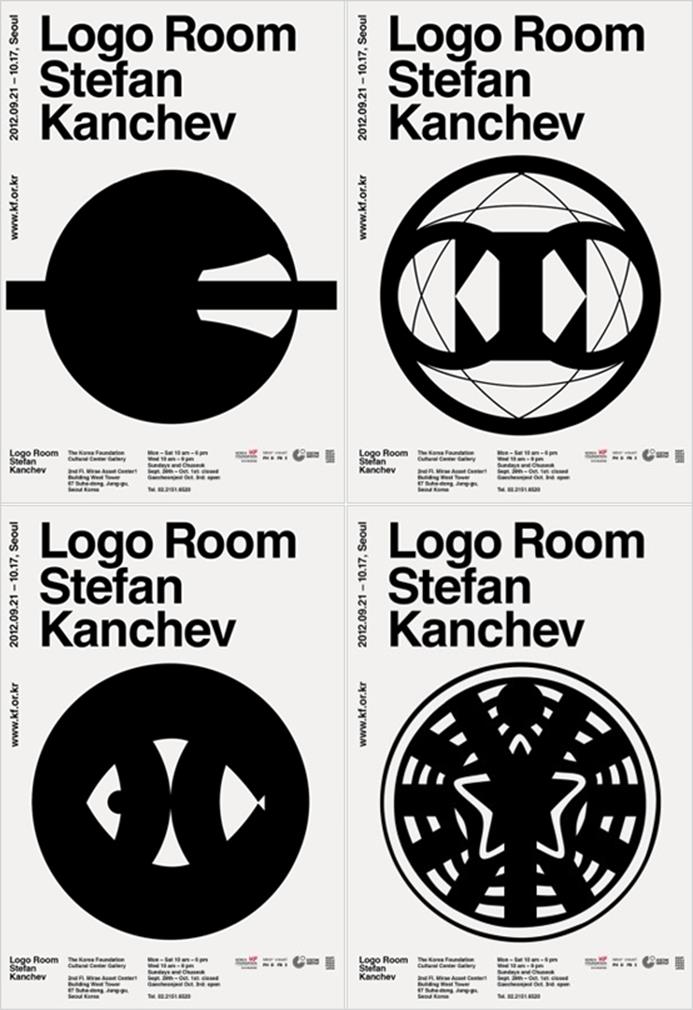
로고 룸 전시 포스터
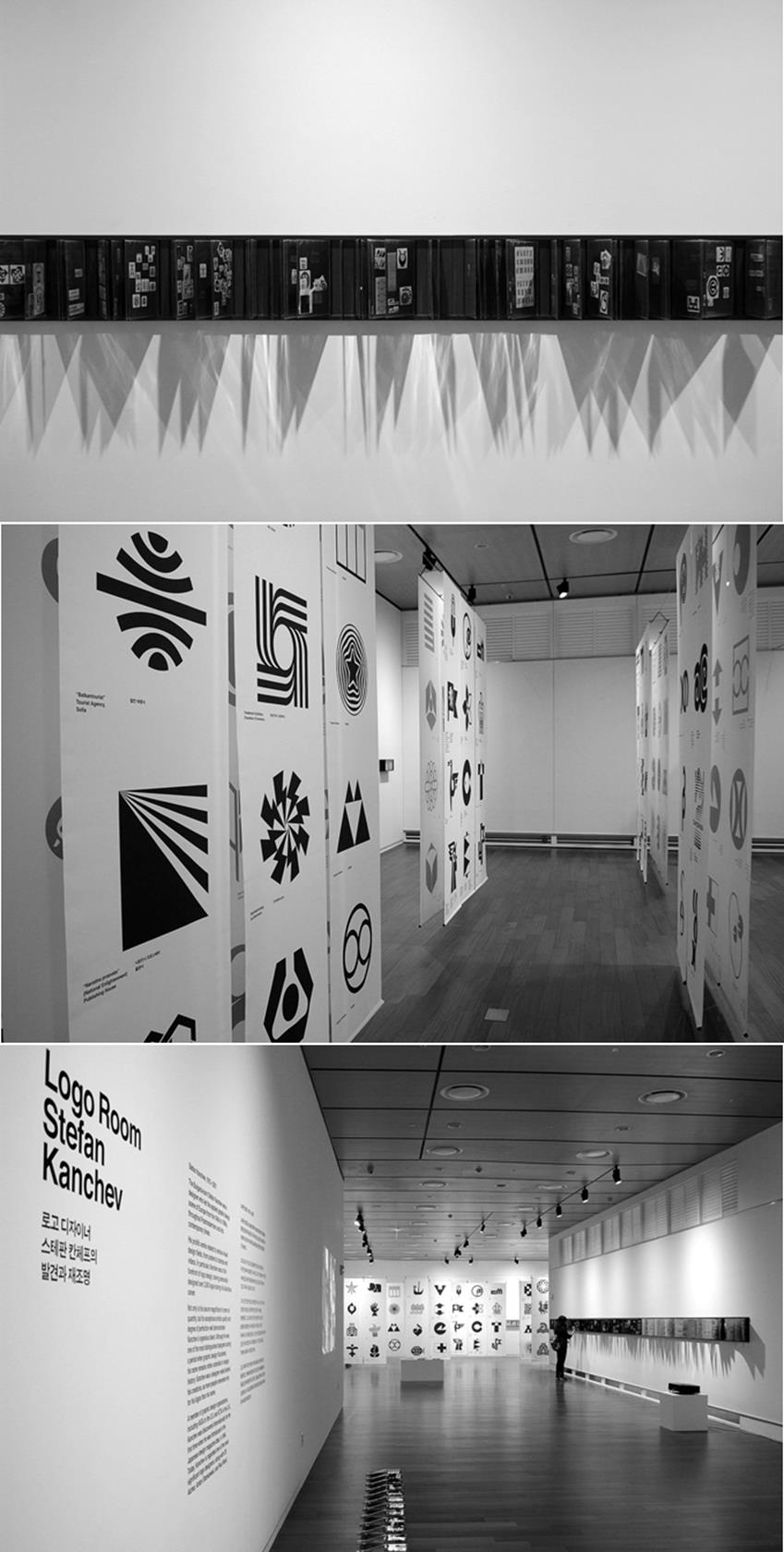
로고 룸 전시장 전경
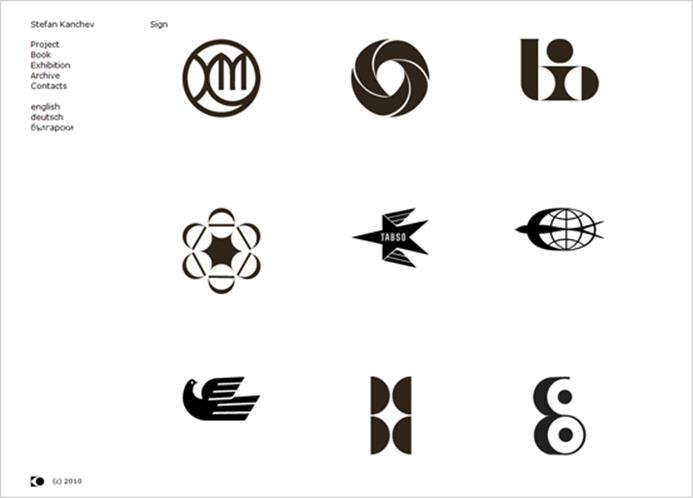
스테판 칸체프 온라인 아카이브(www.stefankanchev.eu)
연구의 주요 과제 중 하나는 스테판 칸체프의 작업들을 아카이빙 하는 것이었다. 체계화 목록화된 디자이너의 작업은 누구나 열람할 수 있도록 온라인 아카이브로 구축되었다. 이 아카이브는 연구결과를 대중과 공유함과 동시에 한 디자이너의 고유한 창작물을 알리고 보호하기 위한 목적으로 진행되었다.
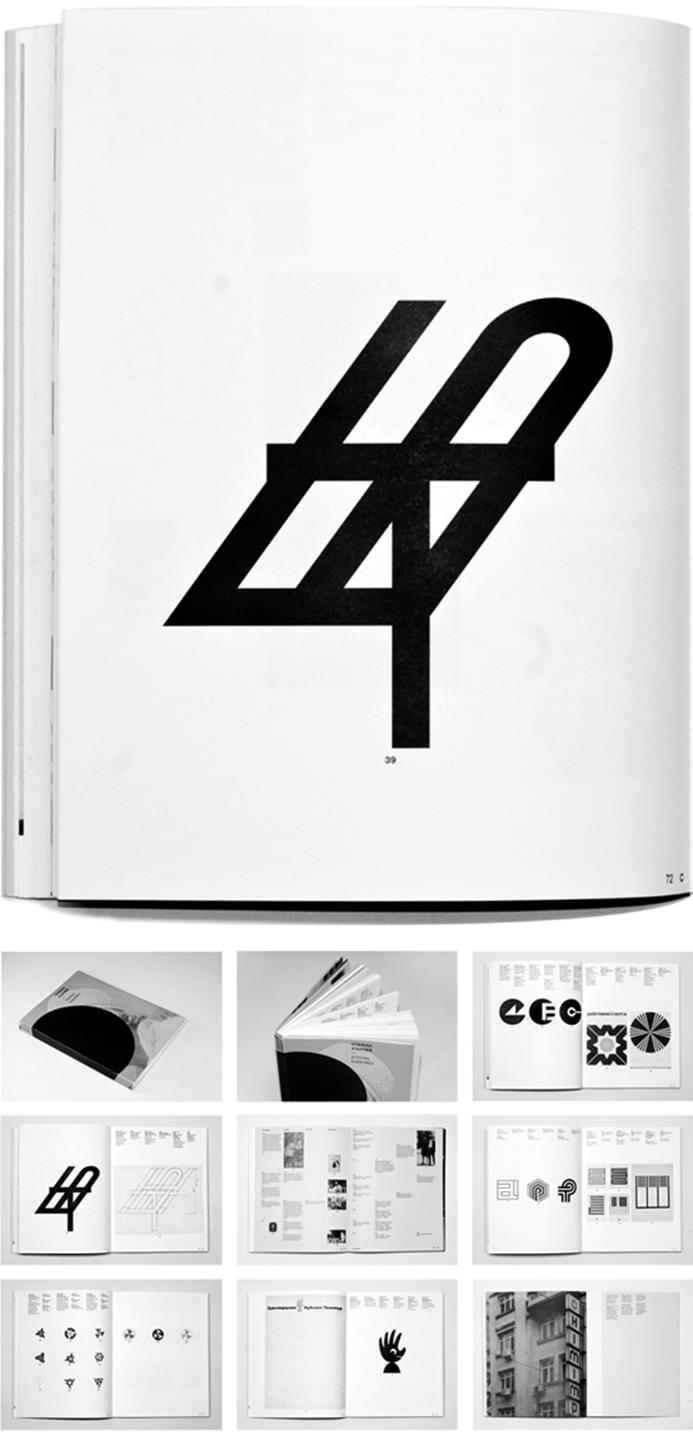
책으로 출간된 스테판 칸체프 연구 결과. 연구 결과를 집약한 이 책은 아카이빙에 적용한 체계를 반영하여 스테판 칸체프의 작업 과정과 그 결과물을 기록했다. 영어, 독어, 불가리아어로 출판되었다.
디자인 역사에 괄목할 만한 업적을 기록하고 오늘날 디자인 교육에 지표가 되는 가치를 이끌어 내고자 한 스테판 칸체프 연구는 라보어비쥬엘의 2006년 헬무트 슈미트 회고전 후속 연구과제로 막달리나 스텐체바의 지도로 이루어졌다. 연구는 스테판 칸체프의 방대한 작업을 수집하는 것으로 시작하여, 그의 작업들을 조형적 기준에 따라 체계화 목록화하는 아카이빙으로 이어졌다. 연구 결과는 2009년부터 전시를 통해 대중에게 공개되고 있으며 2011년에는 책으로 출판되기도 했다.
스테판 칸체프(Стефан Кънчев, 1915-2001)는 1940년대부터 1990년대 말까지 유럽에서 활동한 불가리아 출신의 디자이너로 포스트모던 시대를 거쳐 현대에 이르기까지 유럽의 실용미술을 이끌었던 인물들 중 한 사람이다. 그는 포스터, 우표 그리고 텔레비전 영상 등 다양한 시각 디자인 분야에서 활동했다. 특히 로고 디자인 분야에서 두각을 나타냈고 약 2,500개에 이르는 로고를 디자인하여 ‘로고 디자이너’라 불리기도 한다.
그가 남긴 작업은 양적으로 방대할 뿐 아니라 그 뛰어난 조형성과 완성도로 칸체프의 천재적인 재능과 성실함을 가늠할 수 있다. 그는 그래픽 디자인이 꽃피우던 시절 가장 활발하게 활동했던 디자이너들 중 하나였지만, 디자인 역사에서 그의 이름은 낯선 게 사실이다. 그는 자신의 창조물 뒤에 가려져 있던 디자이너였고 이름보다는 그가 만든 작품들로 기억하는 이들이 더욱 많은 작가 중 한 명이다.
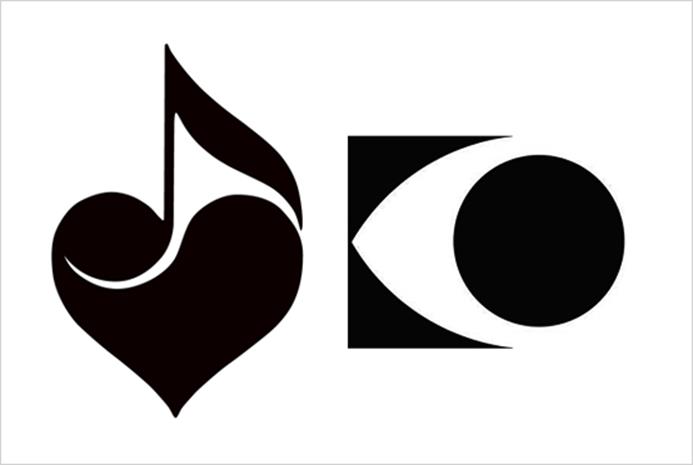
음악 공연장 로고(왼쪽)와 스테판 칸체프가 서명 용도로 사용했던 심볼(오른쪽).
눈을 상징하는 동시에 스테판 칸체프의 머리글자인 키릴문자 C와 K를 형상화 했다.
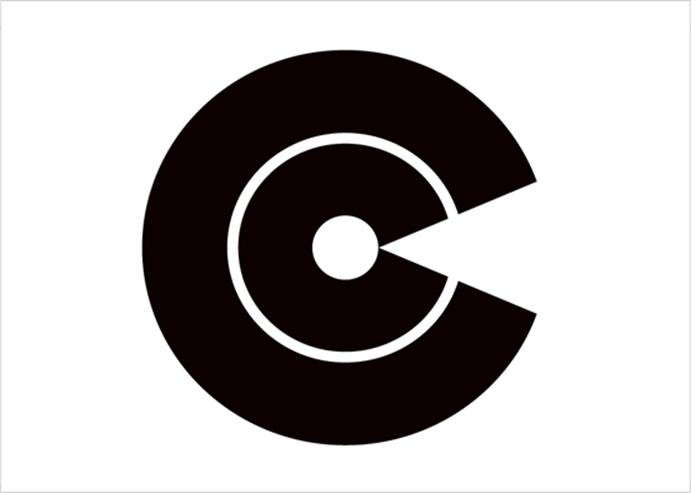
필름 스튜디오 로고. 원은 개방된 부채꼴로 말미암아 원심을 기준으로 시계방향으로 돌아가는 하나의 운동성을 가지게 된다. 이것은 영화라는 매체의 시간성이라는 개념을 형상화한 것이며 또한 눈동자의 형태를 하고 있어 시각매체라는 것을 연상하게 한다. 스테판 칸체프는 두 개 원에 스튜디오 이름의 머리글자 CC를 대입했으며 흰색의 음각 부분은 영사되는 빛을 상징하기도 한다.
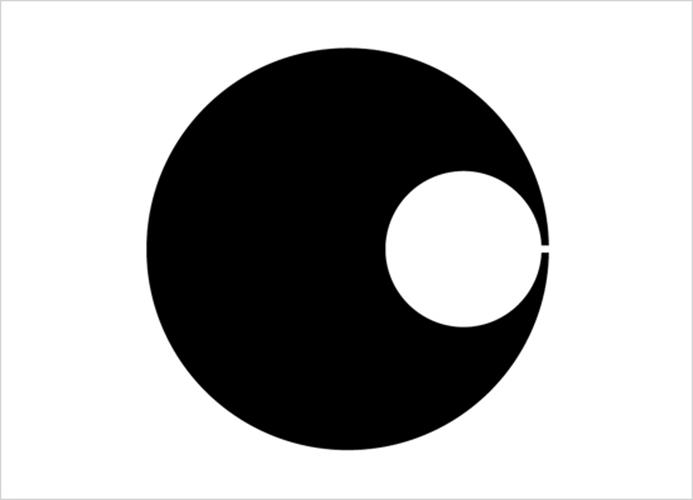
철강회사 로고. 양각과 음각의 두 개 원만으로 파이프를 입체적으로 시각화 했으며, 양가부분의 미세한 개방으로 철강회사 이름의 첫 글자인 C를 표현하고 있다.
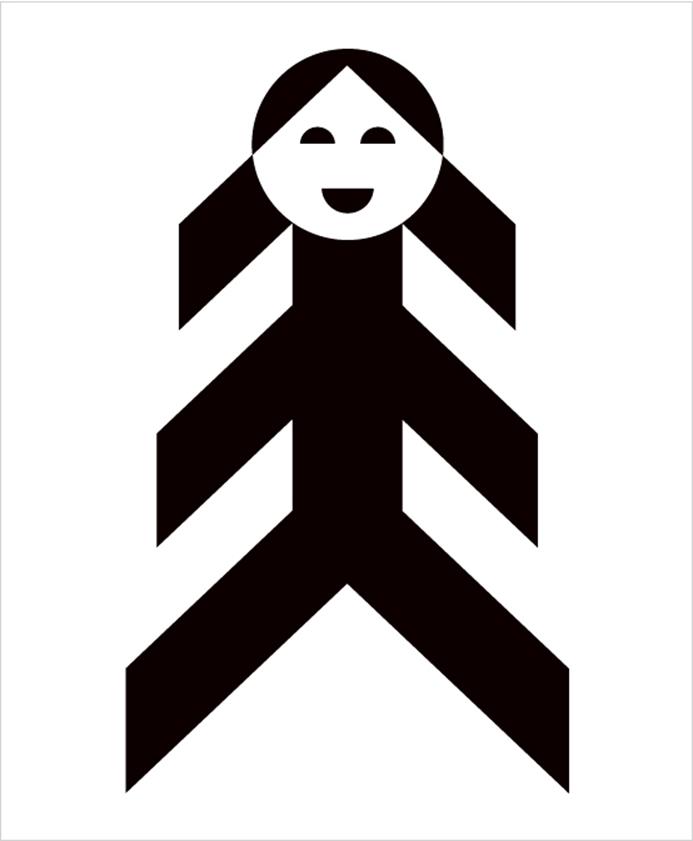
인형극장 로고. 산악 지역에 위치한 한 도시의 인형극장의 로고. 이 지연은 유난히 소나무가 많은 곳으로 유명하다. 형태적 유희는 가장 단순한 기하학적 형태에서 시작함을 보여준다.
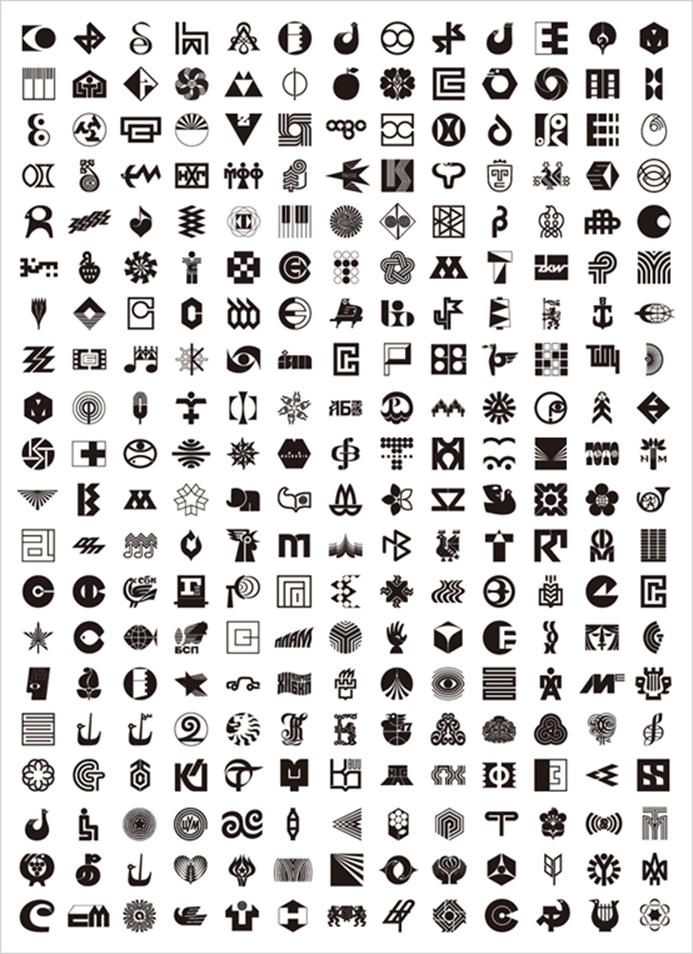
스테판 칸체프의 다양한 로고 디자인 결과물들
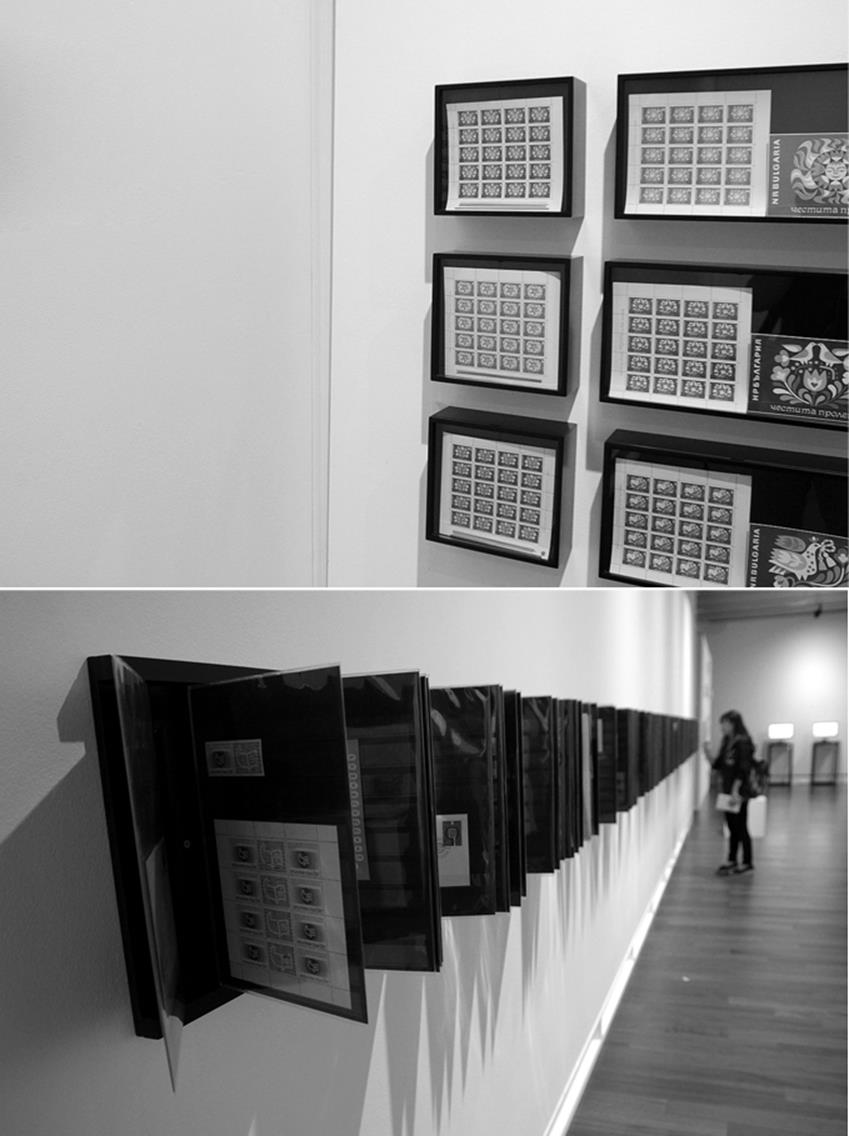
로고 디자인 외에 그의 작업 중 큰 부분을 차지하는 것이 바로 우표 디자인이다. 1946년에 스테판 칸체프는 우표를 디자인하는 첫 위탁을 받았다. 그리고 우표 디자인은 그의 활동기간 내내 지속되었다. 그는 “우표는 어떤 것을 이야기 하기보다는 무엇인가를 의미해야 한다”고 말한 바 있다.
스테판 칸체프는 대상의 정체성과 특성을 오직 형태로 전달하기 위하여 탐구하고 실험한 디자이너로 알려져 있다. 그가 디자인한 로고들은 하나의 형태가 생성하는 가능성에 대해 살펴볼 수 있도록 해주며 점, 선, 면, 음각과 양각, 도형 같은 지극히 기본적인 조형의 원리에서 탄생한 ‘형태’가 다양한 의미전달을 가능하게 한다는 것을 증명하고 있다.
즉, 형태를 그 자체로 인식하게 하는 일차적 시각전달을 떠나 그 형태로부터 내용을 연상하게 하는 지각적 작용을 유도하는 것이다. 또한 그는 평생 컴퓨터 도움 없이 작업한 것으로 유명한데, 하나하나의 로고는 오랜 시간을 거쳐 그의 손에서 탄생한 형태에 대한 탐구이며 그 완벽한 조형성은 스테판 칸체프가 지녔던 장인적 태도를 대변하고 있다.
“I am not much of a speaker.
I am a graphic artist. Whatever I have in mind,
I draw it.”
스테판 칸체프는 그래픽 디자인 단체인 미국의 AIGA와 영국의 ICTA 회원이었고, 1994년에 일본의 디자인 잡지 <이데아>를 통해 처음으로 세상에 알려지기도 했다. 그는 오틀 아이셔, 안톤 스탄코브스키 그리고 폴 랜드 등과 함께 중요한 심볼 디자이너 중 한 명으로 평가 받고 있다